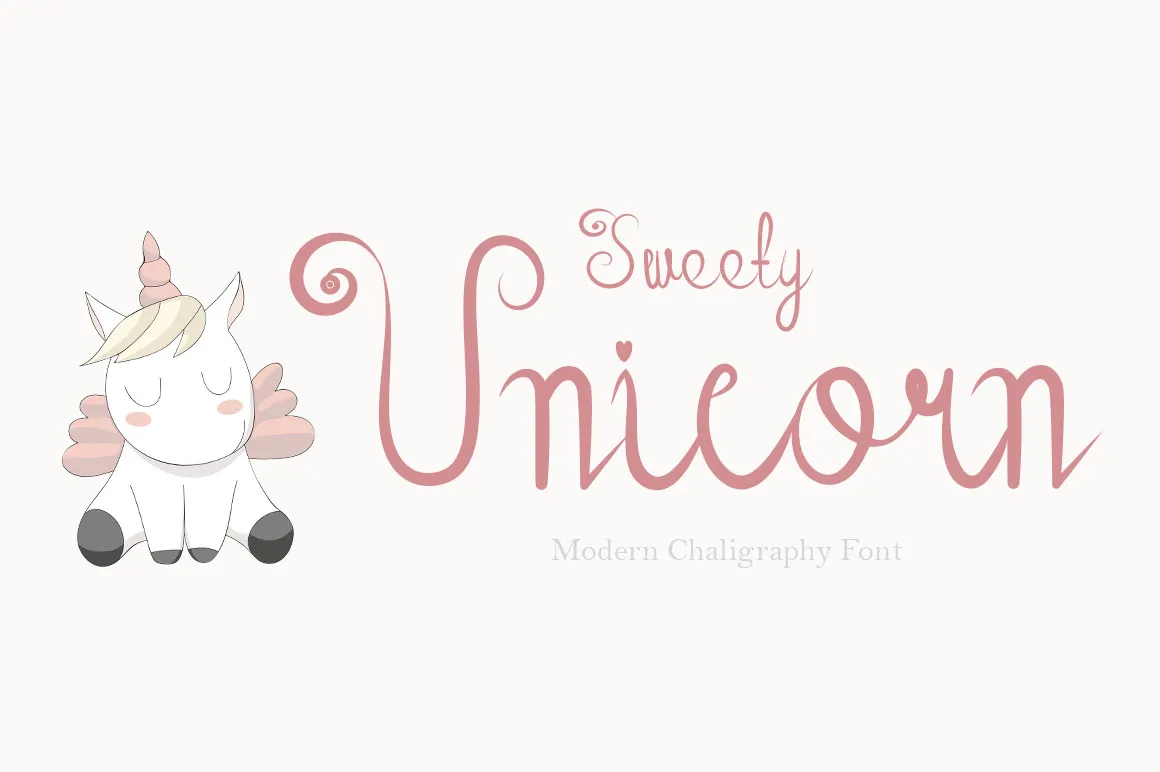
Sweety Unicorn Font – Download Grátis
Sweety Unicorn Font é uma elegante fonte script que transmite sofisticação e elegância com seu estilo refinado. Seus alternantes estilizados e ligaturas sofisticadas fazem deste fonte a escolha perfeita para qualquer projeto, seja ele um relatório de trabalho formal ou um cartão de aniversário cheio de vida. Este design criado por Muhamma Zamroni é uma grata surpresa para designers que valorizam tanto o charme quanto a funcionalidade. Agradável e atemporal, Sweety Unicorn Font combina arrependimento com modernidade, ideal para qualquer ambiente onde desejaria um toque diferente de unicórnio elegante em seu trabalho ou arte. Não hesite em explorar essa fonte elegante que traz vida à sua criação, seja ela uma pequena marca no papel até a capa de um livro de design gráfico.
Designer: Muhamma Zamroni